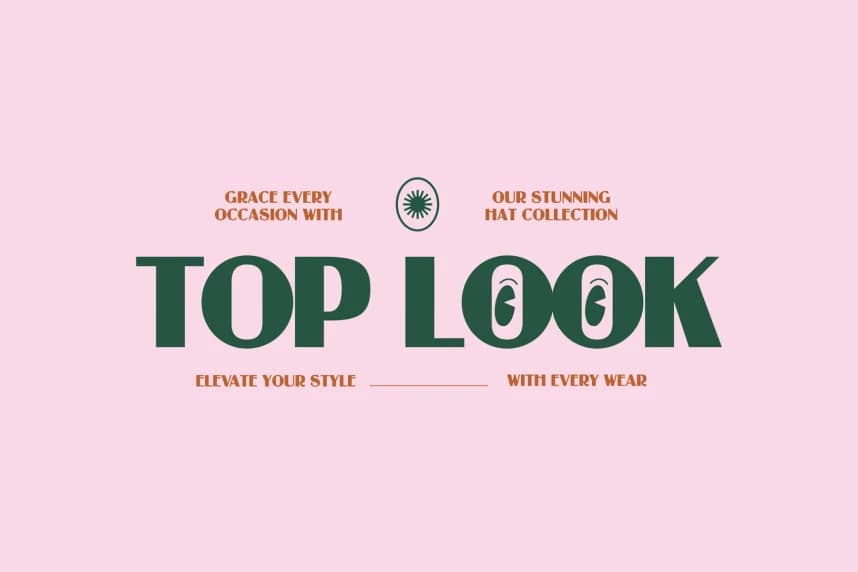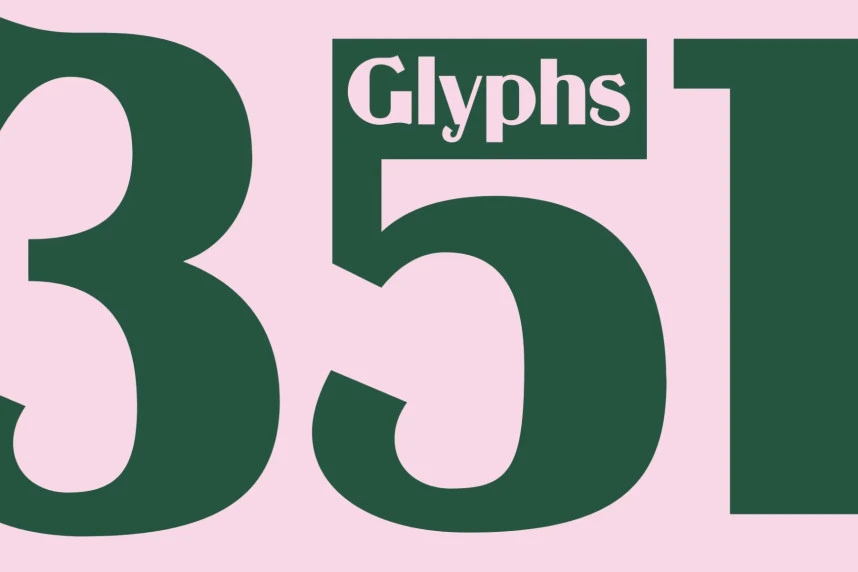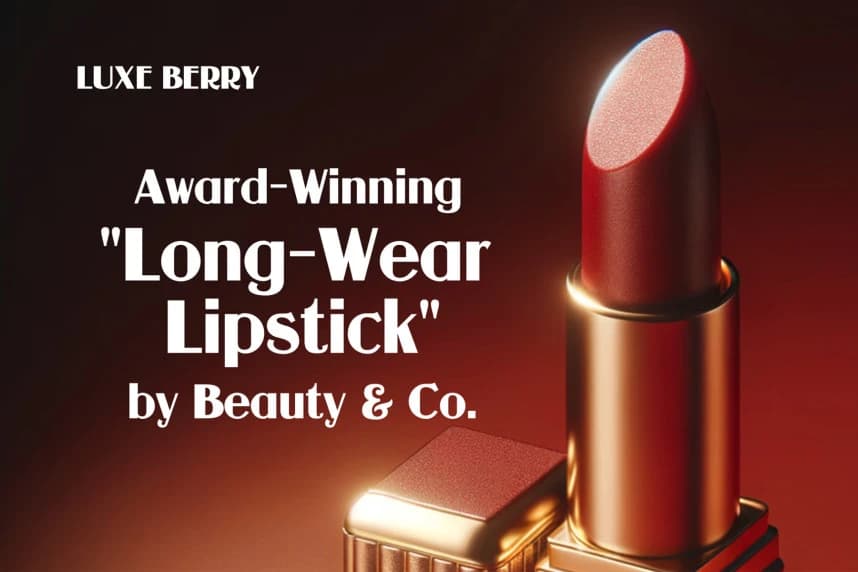
Monava Font
Monava Font, zamansız tasarımı modern bir dokunuşla takdir edenler için özenle tasarlanmış zarif ve sofistike bir sans-serif yazı tipidir. 351 titizlikle tasarlanmış glifler ve 90'dan fazla dile sahip çok dilli destek ile Monava, küresel yaratıcılar için eşsiz bir çok yönlülük sunar.
Monava Font, zamansız tasarımı modern bir dokunuşla takdir edenler için özenle tasarlanmış şık ve sofistike bir sans-serif yazı tipidir. 351 özenle tasarlanmış glifler ve 90'dan fazla dil için çok dilli destek ile Monava, küresel yaratıcılar için eşsiz çok yönlülük sunar.